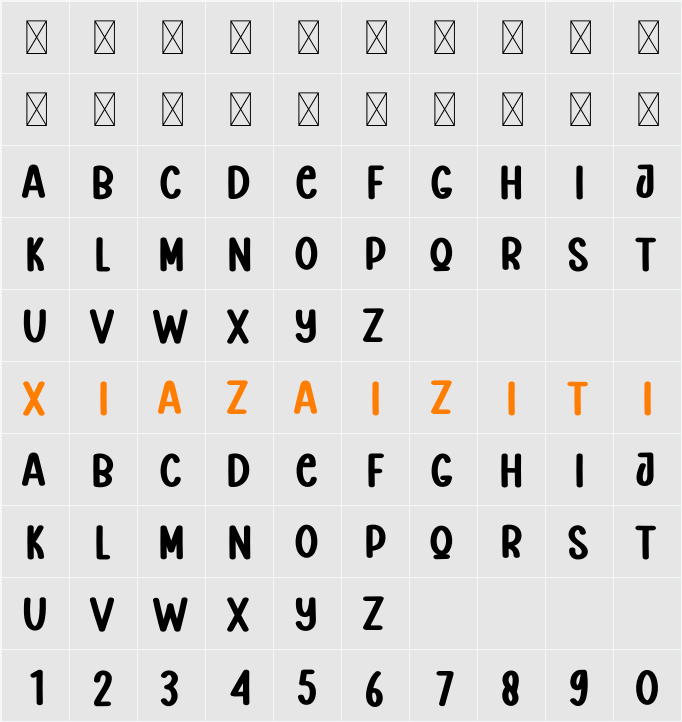
Winter Sweeter
Winter Sweeter,这款字体结构工整、笔画清晰,兼顾美观与易读性,适用于标题、正文、海报、包装、LOGO 等多种场景。字形优雅稳定,风格百搭耐看,适配日常排版与创意设计,让文字呈现更舒适、更具质感。Winter Sweeter一笔一画,皆是细节,以均衡的比例、流畅的线条打造舒适视觉体验,字形端正大气,风格简约现代。无论是商业设计、品牌宣传还是日常排版,都能轻松驾驭,让文字更有格调与力量。Winter Sweeter字体下载。